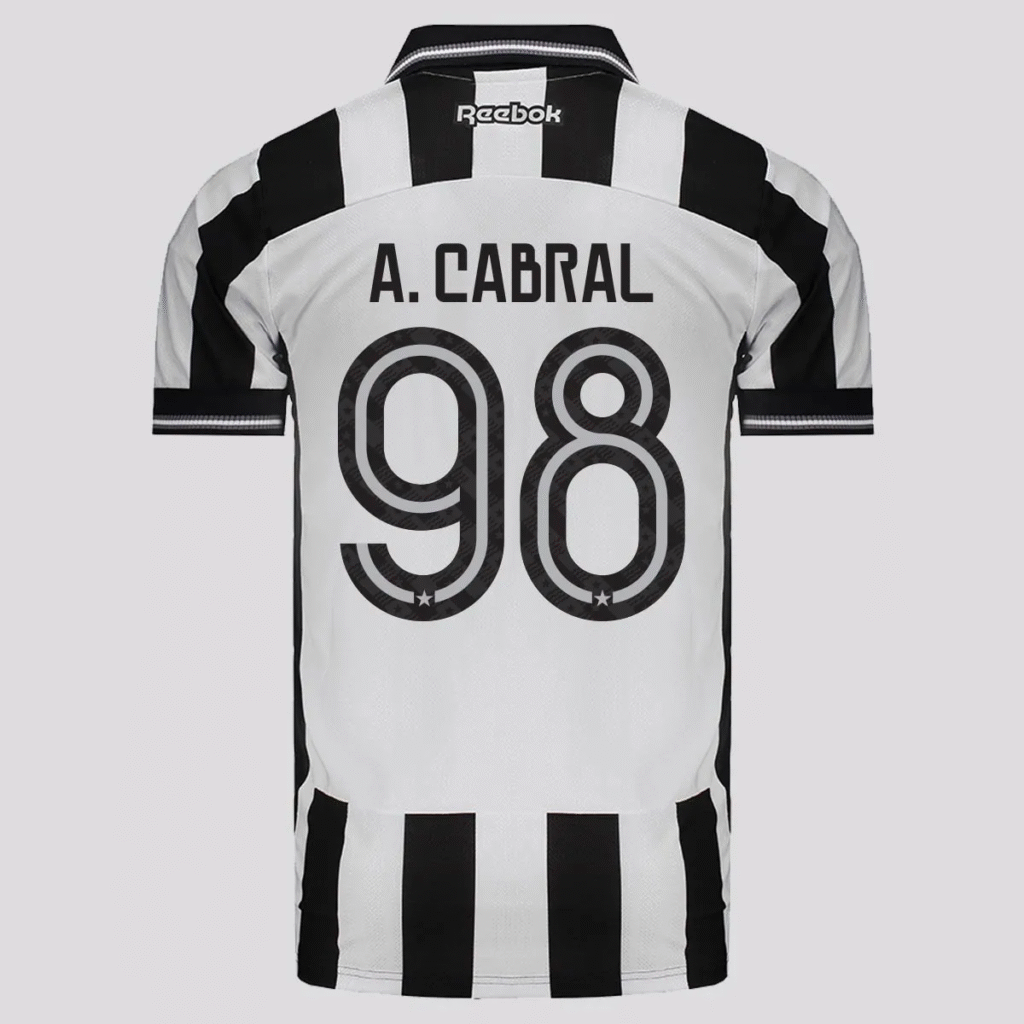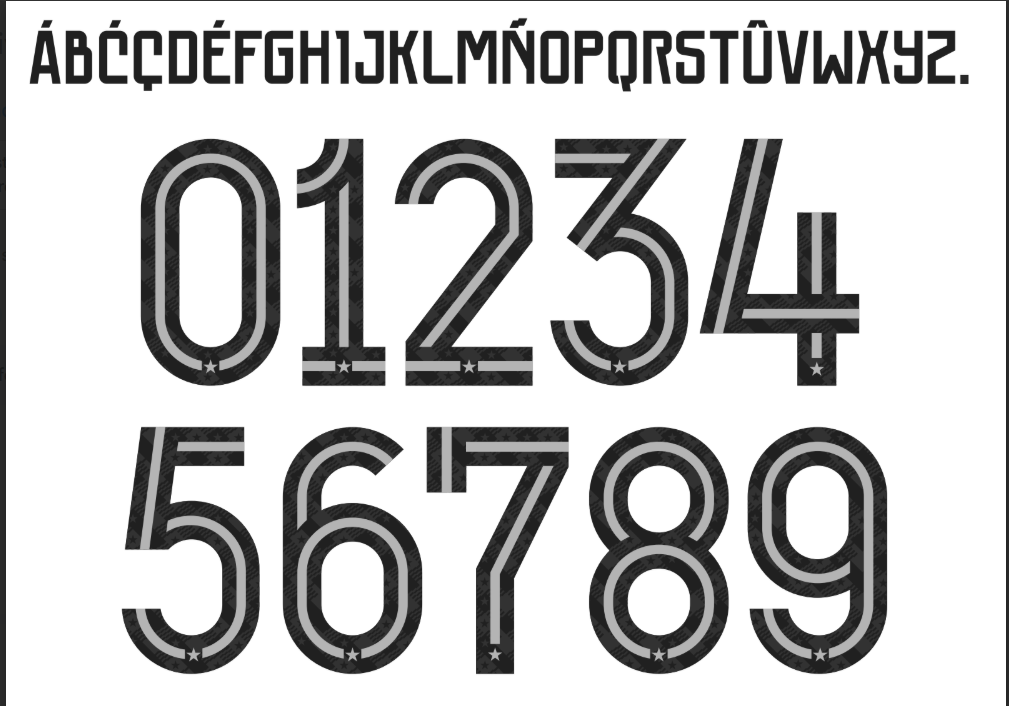
A temporada 2025-2026 chegou, e com ela, a nova identidade visual que vai vestir o Botafogo nos gramados. A torcida alvinegra, sempre apaixonada, sabe que cada detalhe do manto é importante, e a tipografia usada nos nomes e números dos jogadores é uma parte crucial dessa identidade.
Seja você um designer criando artes para redes sociais, um torcedor querendo personalizar uma camisa ou um entusiasta do branding esportivo, ter a fonte correta é essencial. Esta é a tipografia que estampa a garra do “Fogão” em campo.
A fonte do Botafogo para 2025-2026 (potencialmente desenhada em parceria com a fornecedora de material esportivo) combina modernidade com a tradição do clube. Ela apresenta linhas limpas, um design ligeiramente robusto e cortes geométricos que garantem excelente legibilidade, tanto na TV quanto ao vivo.
Essa tipografia transmite força e seriedade, alinhada à história do “Glorioso”. Ela é usada em todo o conjunto de uniformes (principal, reserva e alternativo) durante as competições da temporada, como o Brasileirão e, quem sabe, a Copa Libertadores.